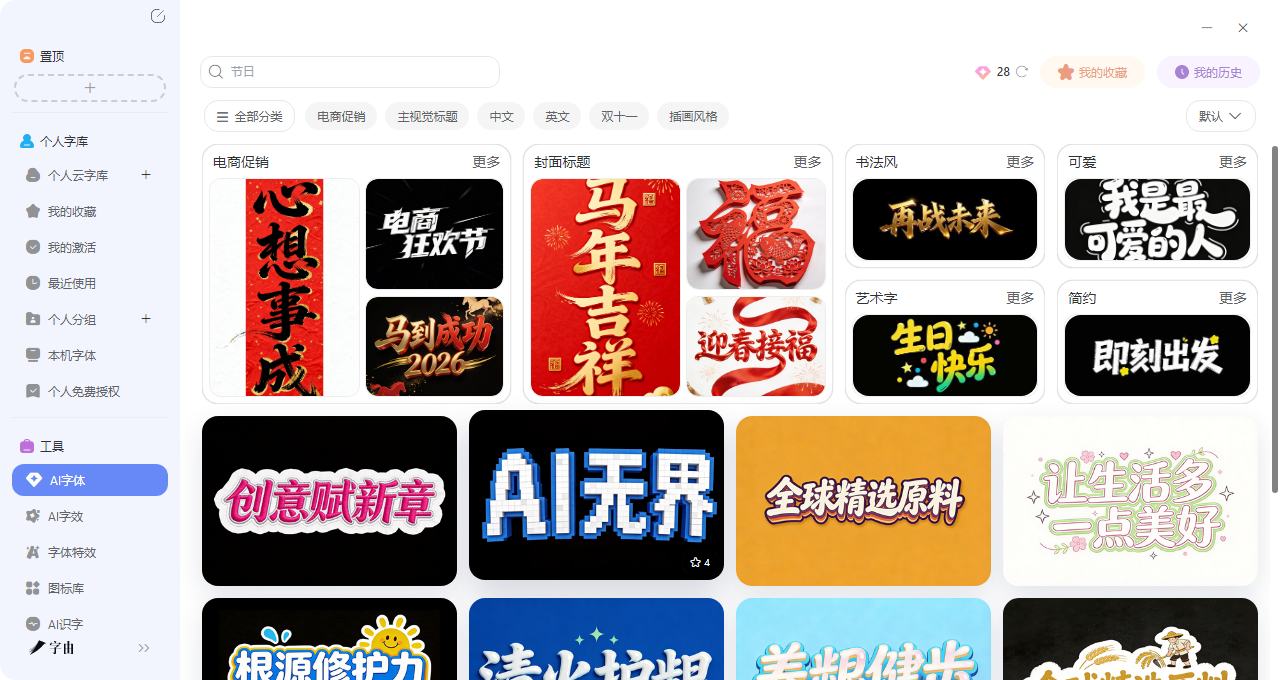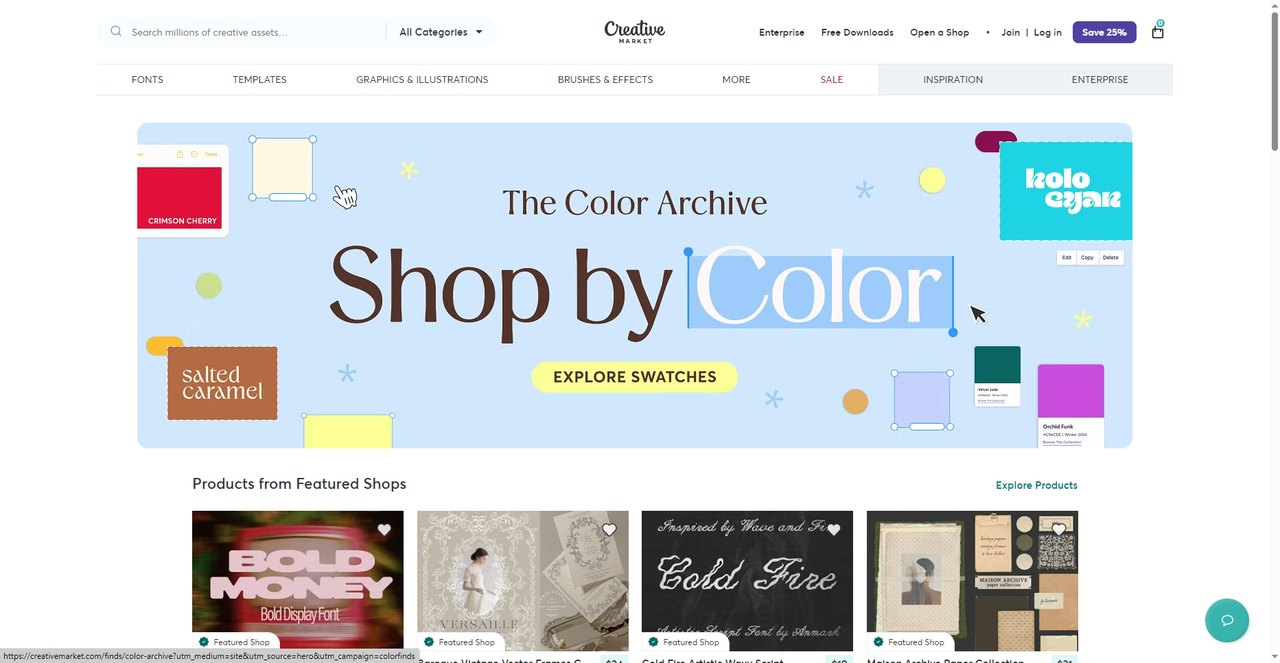
产品包装不够高级?可能是文字没选对:包装文字设计工具推荐
我们在购买商品的时候,肯定会先注意它的外包装,那些让你心动的包装,往往不是构图多复杂,而是在包装上的字体起着关键作用,茶叶罐上的书法体透着禅意,香水瓶上的花体字写着优雅,零食袋上的可爱字让人想立刻拆开。包装上的文字,就是产品递给顾客的第一张名片。如果是普通的产品还好,但是如果你有更高的需求,想做一套有质感的产品包装设计,肯定是要请设计师花几千块的。但是现在我们有了产品包装文字设计工具,让你输入文字就能一键生成。那么今天我就会介绍 4 个亲测好用的产品包装字体工具。
你有没有想过,那些摆在货架上的爆款产品,包装上的字可能是用字由做出来的?最近我在字由的AI字体里搜了一下“电商促销”和“主视觉标题”,结果发现了一堆宝藏模板。而且字由的AI字体应用特别简单,只需要不超过五步就可以完成,那么接下来我会教大家具体的步骤来免费生成产品包装字体,也会附上一些需要注意的细节:
第一步:进入AI字体页面后,在搜索框里输入“包装”“电商”“促销”“节日”等关键词,系统会自动筛选出所有适合做包装文字的模板。你也可以试试“主视觉标题”。
第二步:搜索结果会展示各种风格的预览图,每个模板都有独特的设计:
- 喜庆吉祥类:“心想事成”“马到成功”这种,适合年货、礼盒
- 现代促销类:“电商”“狂欢节”这种,适合快消、爆品
- 艺术装饰类:“艺术字”这种,适合文创、设计师款
- 科技潮流类:“再战未来”这种,适合数码、潮玩
- 温馨手写类:“生日快乐”这种,适合生日礼盒、派对
- 简约高级类:“简约”这种,适合护肤品、香薰
第三步:点击选中的模板,进入编辑页面。在输入框里填你想生成的文字,比如产品名、品牌名、广告语。
第四步:确认文案后,点“立即生成”,等20-30秒左右就能拿到图。生成后可以预览效果,不满意就换其他模板再试,或者微调文案重新生成。每天有免费算力点,日常试用完全够用,
第五步:生成后直接点击保存就可以了。
所以,别再做包装时对着空白的PS发呆了。打开字由,搜个“电商促销”,翻翻那些藏在分类里的宝藏模板,选一个顺眼的,填上产品名,几十秒就能拿到一张能用的包装文字图。
除了以上的步骤,我还有一些关于产品包装字体的指南,喜欢的可以花一点时间看一下:
- “心想事成”“马到成功”:这两个模板是喜庆吉祥的书法风格,字体重,有力量,带着传统韵味。适合做年货礼盒、节日限定、文创产品的包装。大红底色配上烫金效果,年味儿十足。如果做茶叶、糕点、对联礼盒,用这种字体准没错。
- “再战未来”:这个模板是科技感风格,字体硬朗,有未来感。适合做数码产品、潮玩、运动品牌的包装。年轻化、有态度,很对年轻人的胃口。
- “我是最可爱的人”:这个模板是活泼的卡通风格,圆润可爱,充满童趣。适合做儿童产品、零食、宠物用品的包装.
2、The Color Archive
The Color Archive 是一个创意字体集市,它专门按颜色分类展示字体和设计资源。不难看出,主页里它推荐了多款适合包装设计的字体:
- Bold Money - Bold Display Font:粗体显示字体,力量感强,适合做高端礼盒、限量版的包装标题。
- Cold Fire Artistic Wavy Script:波浪形艺术手写体,有动感,适合做酒水、饮料的包装文字。
3、Fonts for Packaging and Labels
这个网站比较专业了,是一个专门为包装和标签设计的字体平台,它精选了多款适合包装场景的字体,每款都强调在小空间里的可读性和视觉冲击力。虽然这些字体都需要购买授权,但是对于追求专业品质的包装设计来说,是很好的选择。
4、Fontspace
在Fontspace 里有2248 款免费包装字体,几乎覆盖了所有包装可能用到的风格。比如说:
- Believe Stronger:由zeenesis studio设计,免费个人使用。字体粗壮有力,适合做运动品牌、功能性产品的包装标题。
- Vegan Style:由Billy Argel Fonts设计,免费个人使用。字体清新自然,适合做素食、有机食品的包装。
每款字体都有下载次数和用户评分,可以帮助你快速判断受欢迎程度。如果你需要品牌字体的免费资源,这个平台会很适合你。
话说回来,产品包装上的字,就是产品递给顾客的第一张名片。看完以上的产品包装文字设计工具推荐,相信你已经有自信多了,尤其是字由,直接把设计的难度拉到了最低,只需要打开客户端,搜个“电商促销”,翻翻那些藏在分类里的宝藏模板,选一个顺眼的,填上产品名,等几十秒,能上货架的包装文字就在那了。就我看来,字由无疑是最好的选择。